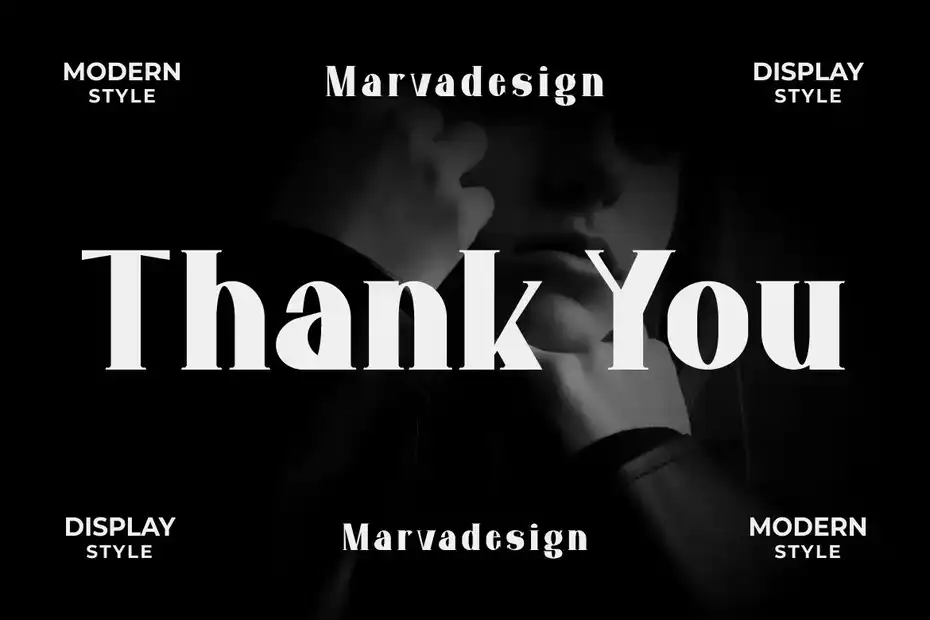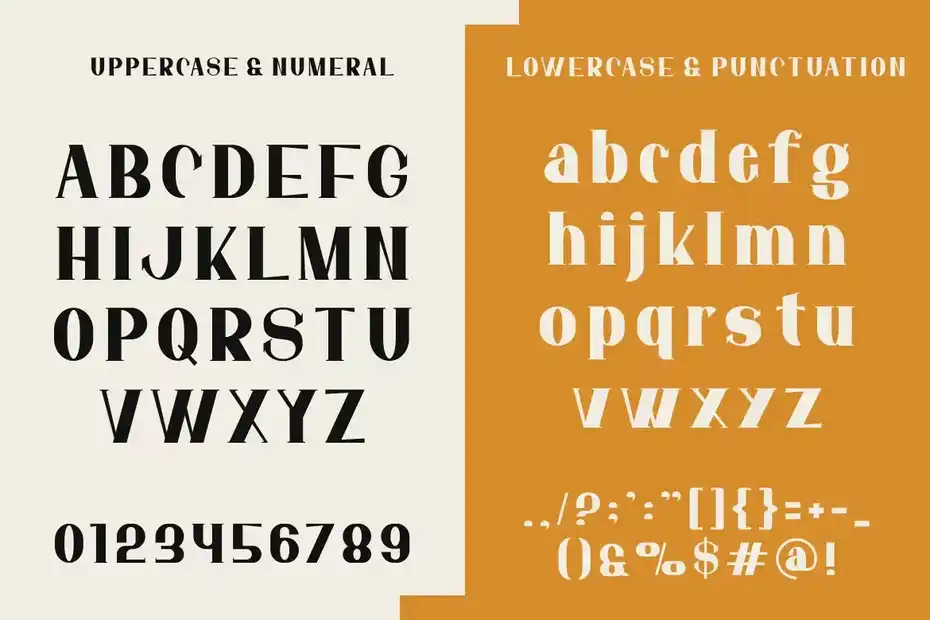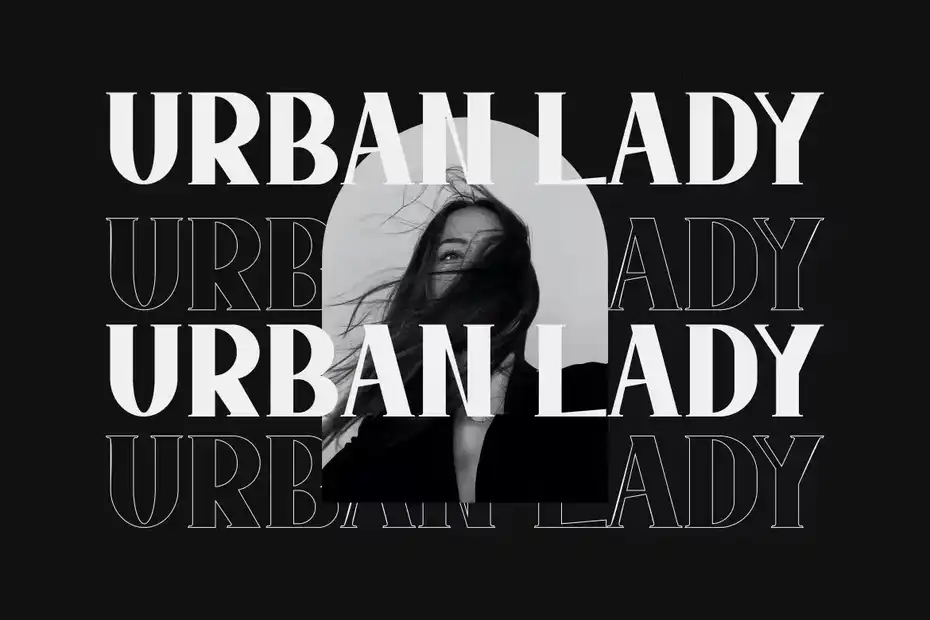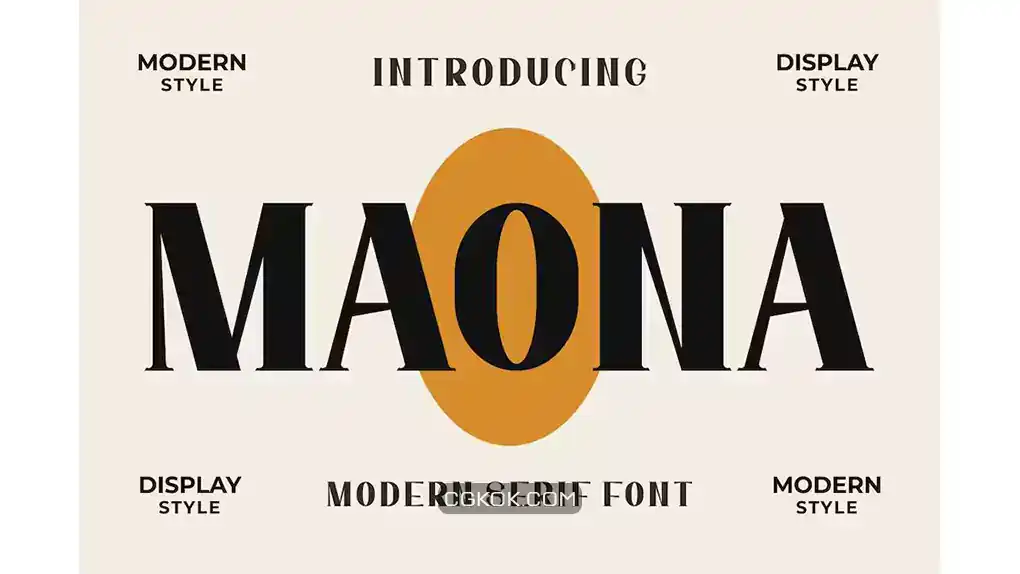
فونت انگلیسی MAONA Font : این فونت یک فونت نمایشگر برجسته و معتبر است که برای پروژه های برندسازی مانند: لوگو، چاپ تیشرت، محصول و غیره مناسب میباشد.
- سبک: Serif
- فضا بین حروف: معمولی